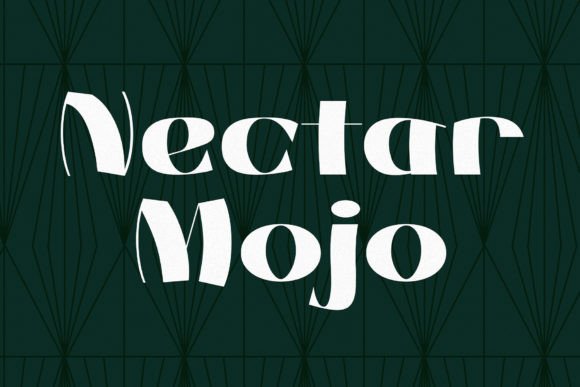
Nectar Mojo
Nectar Mojo – A Tipografia Vintage que Revive o Glamour Art‑Deco
Se você procura uma fonte que transporte seu projeto direto para os salões de jazz e os elegantes cocktail bars dos anos 20, Nectar Mojo é a escolha certeira. Criada como uma homenagem ao Art Deco, ela combina linhas geométricas, curvas sofisticadas e detalhes ornamentados que dão vida ao luxo e à ousadia da era do roaring twenties.
Por que Nectar Mojo se destaca?
- Design autêntico Art‑Deco: Cada caractere foi inspirado nas formas geométricas e nas superfícies polidas que definiram a estética dos anos 1920.
- Versatilidade moderna: Apesar da pegada vintage, a fonte possui espaçamento e legibilidade otimizados para uso digital e impresso.
- Detalhes ornamentais: Traços finos e refinados adicionam um toque de opulência sem sobrecarregar o layout.
- Aplicações amplas: Ideal para branding de marcas premium, embalagens de luxo, capas de revistas, convites de gala ao estilo Gatsby e cartazes de clubes de jazz.
Experiência de uso
Ao aplicar Nectar Mojo em um logotipo, a marca ganha instantaneamente um ar de exclusividade e nostalgia, perfeito para negócios que desejam comunicar tradição e sofisticação. Em projetos editoriais, a fonte cria hierarquias visuais elegantes, guiando o leitor com clareza e estilo. Já em embalagens, seus detalhes decorativos transformam simples rótulos em verdadeiras peças de colecionador.
Para quem é indicada?
- Designers que trabalham com identidade visual de marcas de alto padrão.
- Agências de publicidade que desenvolvem campanhas com temática retro ou vintage.
- Estúdios de design de eventos que organizam bailes, festas temáticas ou lançamentos de produtos luxuosos.
- Editoras que buscam um toque elegante para capas de livros ou revistas de moda e arte.
Nectar Mojo não é apenas mais uma tipografia vintage; ela é um portal para a era dos flappers, do jazz e da extravagância dos anos 20. Seu equilíbrio entre charme histórico e funcionalidade contemporânea a torna indispensável para quem deseja acrescentar timeless elegance a qualquer projeto. Experimente Nectar Mojo e deixe seus designs brilharem com a sofisticação que só o verdadeiro Art Deco pode oferecer.